“创造书法新世界”字体家生态构建者峰会暨《纵横体》字体发布会在太极禅苑举行
10月27日下午,“创造书法新世界”字体家生态构建者峰会暨《纵横体》字体发布会在太极禅苑举行,络绎不绝的嘉宾如约而至,他们有的聚集在活动背景墙前欢乐合影,有的即兴挥毫泼墨尽展书法风范。一身时尚装扮的叶根友,文质彬彬,蔼然可亲,正所谓人逢喜事精神爽!
发布会在太极禅苑副院长羽真端庄、大器的主持下,拉开帷幕。
叶根友行云流水地书写空心字《创造书法新世界》,顿时,赢得满堂彩!
叶根友分享了“创造书法新世界”的机缘,源是受到陈伟院长“企业家要有海纳百川的格局“点化,从而联想到自己曾在初一时,就梦想能够拥有个人书法字体。如今,叶根友通过十多年的努力奋斗,实现了心愿。在互联网如此发达之际,他想通过自己的力量,帮助更多的书法家和喜欢书法的爱好者实现“拥有个人字体”的愿望。
太极禅苑陈伟院长分享了自己的“纵横体”及其在开发字体过程中的喜忧心情。他鼓励大家积极参与,勇于尝试书法创新,在拥有个人书法字体的同时,亦无愧于面对祖先传承的中国书法文化。
创意不断,在书法字体上一直坚持“不走寻常路”的叶根友,目前研发出多种创新方式的字库体裁,目标是创作出几千个字体。为了目标,“叶根友无界字形研发中心“诞生了!太极禅苑院长陈伟、字体家平台创始人叶根友、杭州贤书阁文化创意有限公司运营经理程东、唐曾平设计创始人唐曾平,易象策划毛红有,一起为“研发中心”揭幕。
字体家平台于2018年5月20日成立,现合作的书法家已达212位。来自五湖四海的书法家、律师、程序员、学生等不同身份的艺术家相聚在字体家平台,不仅成功发行了个人字体,收获了良好的口碑和反响,也为自己的书法生涯画上了浓墨重彩。合作艺术家获奖人有:沙剑甬,刘一秋,刘荣月,鲍贵芬,王轩,梁海,张宇星,叶利航。大家纷纷表示,创造出独具风格的个人字体,才能让书法更接地气,更聚人气!
此前,字体家平台和杭州之江实验外语学校举行的手写体“创造书法新世界”活动,88幅创意新颖、遒美娟秀的参赛作品,凝聚了孩子们对书法文化的热爱。字体家平台与杭州师范大学举行的手写体“创造书法新世界”活动,68幅参赛作品里,不仅有刚正不阿的楷书、潇洒飘逸的行书,还有与英文相结合的创意书法。通过这样的书法竞赛,同学们不仅感受到书法文化的博大精深,同时还涌现出大大小小的“书法家”。
由字体家平台创始人叶根友、唐曾平设计创始人唐曾平、易象策划毛红有、深圳高景贺律师担任台上嘉宾的字体家生态构建者峰会,围绕书法字体版权保护展开激烈讨论。高律师和裴律师谈及,我国法律对于计算机刻画出来的美术字和类似字体家平台上出自艺术家之手的富有创新、美感的字体实施保护。据悉,我国司法体系鼓励艺术家得到市场认可,对于艺术家们提供的社会价值和经济价值,正在加大保护力度。
唐曾平设计师现场呼吁:尽快告别对书法严丝合缝的临摹旧世界,尽早走进书法新世界释放个人特色,完成从自我到超我的突破过程,这才是真正的现代书法家!
台下的来宾,对于我国目前IT界和广告界玩盗版,玩抄袭,整个设计界玩字体不愿付费的现象畅所欲言,但“知识产权版权保护,越来越受到重视“日趋明朗的大环境之下,大家亦保持积极乐观态度。
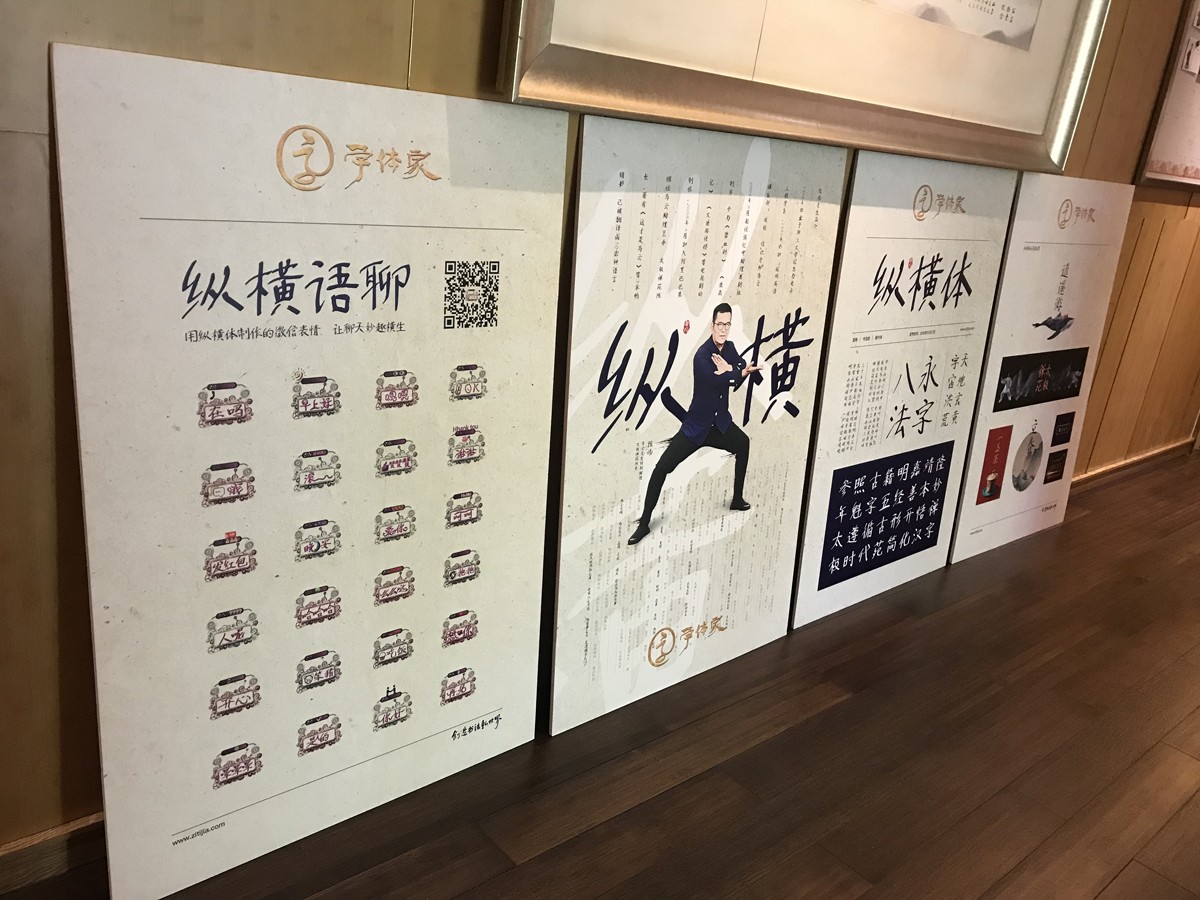
“创造书法新世界”字体家生态构建者峰会暨《纵横体》字体发布在社会各界人士的热烈掌声中圆满结束。此次活动,来宾们不仅受到书法文化的洗礼,还了解书法家字体平台是一个予人梦想的平台。它激发、保障艺术家的创作动力,它实现创造者的个人价值和社会价值!期待字体家平台汇聚更多的优秀人才,在书法领域里,真正做到每个艺术者都是创造者,每个消费者都是参与者。创意无限,新作不断,海纳百川,举世瞩目!(作者:于辉)